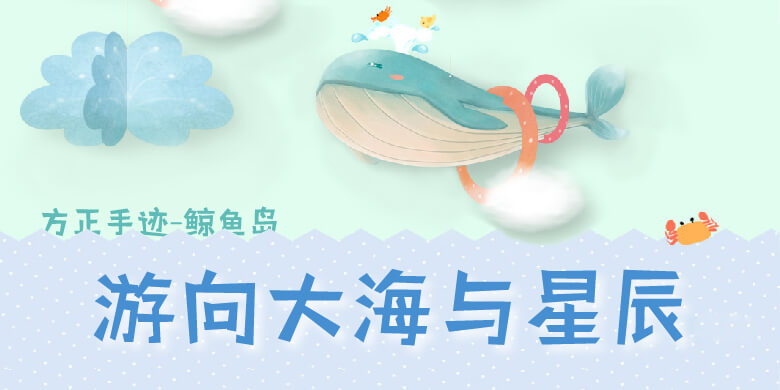
品牌:方正手迹 设计师:刘晔发行时间:2018字库编码:大陆简体(GB2312-80)分类:创意书写
字体设计灵感来自日本漫画,未来的人们在海洋覆盖了地球之后,心安理得的住到了一头巨大的鲸鱼身上。“鲸鱼岛”一个颇具浪漫气息的名字,一个超人气的虚拟乐队,一款未来感十足的字体。适用于少年儿童类的书刊、品牌广告和产品包装设计,以及社交网络的个性化用字。